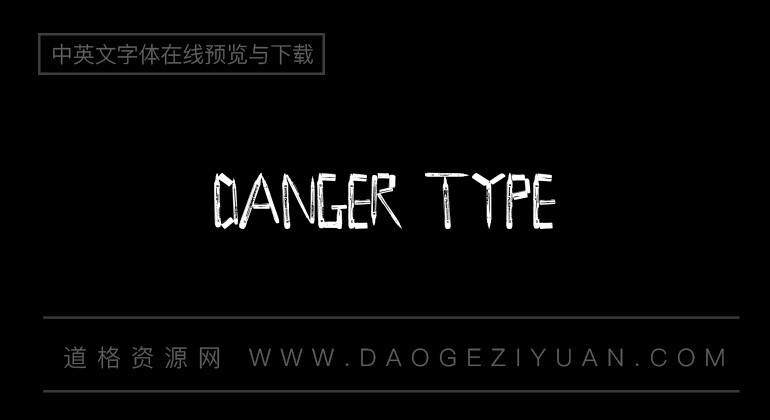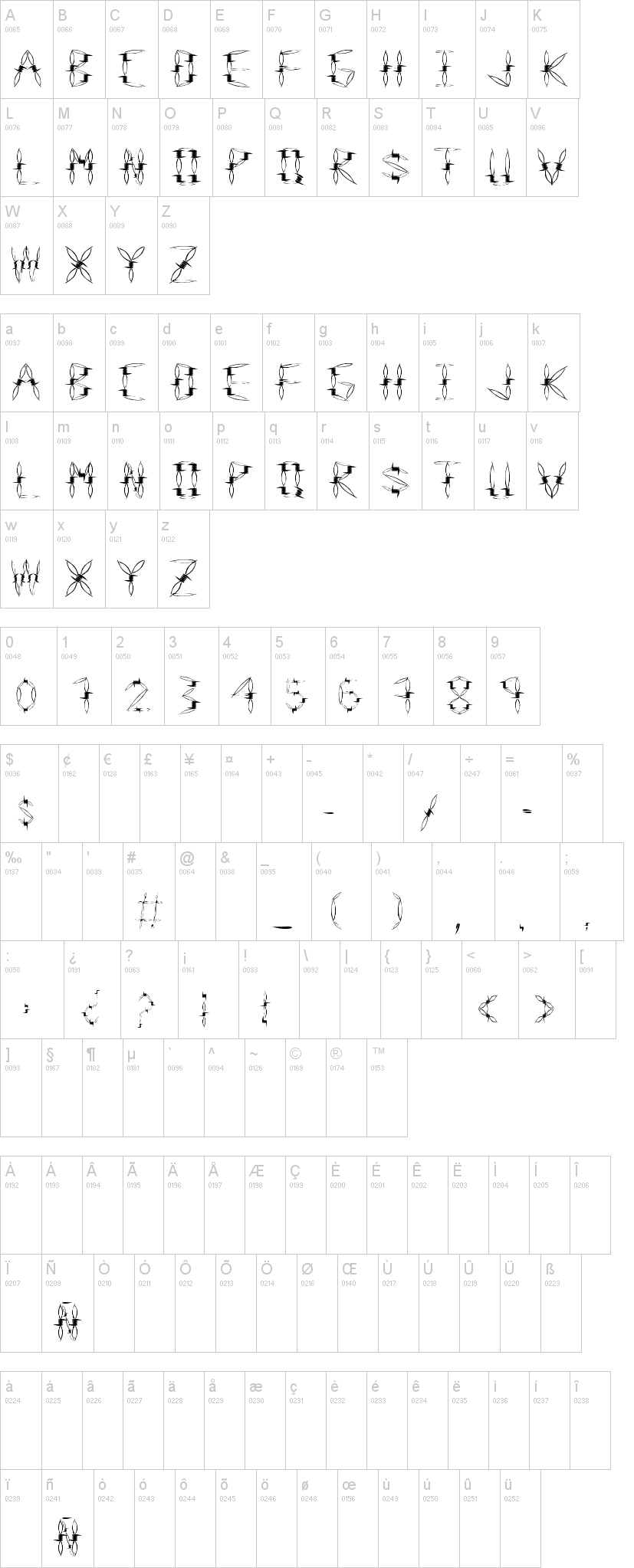
Danger Type 是一款具有古典复古风格的字体,它的字形精致而特别,具有浓浓的复古气息。它的字体设计简约而不失古典气息,看上去很有质感,是一款非常适合用于报刊、海报、流行品牌等类型设计的字体。它的字体结构设计精致,可以提供更多的可读性,而且具有更好的视觉效果。内容介绍
Danger Type是一款非常不错的手写艺术字体,具有很好的视觉感,适合于文化类的宣传设计、商业类品牌的广告和产品包装设计以及个性化文字排版等较多场景。